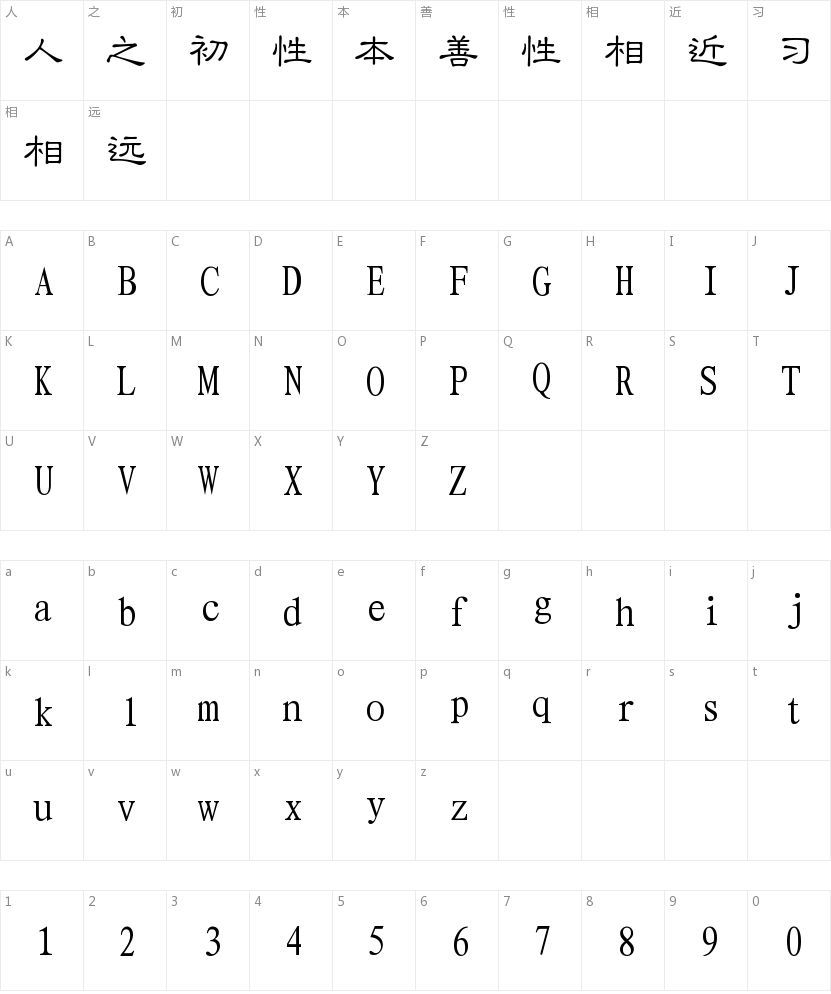
经典隶变
经典隶变字体是一种汉字字体,它的设计灵感来自古代汉字的结构和形式,在保持古典风格的同时,又有一定的现代感。经典隶变字体的字形比较粗犷,字体结构比较简单,字体之间的间距比较大,字体的笔画粗细比较均匀,字体的视觉效果比较稳定,整体显得比较端庄。经典隶变字体适用于品牌标识、书籍封面、文档排版等场景,具有较强的视觉冲击力,能够给读者带来良好的视觉体验。
经典隶变是一款非常不错的手写艺术字体,具有很好的视觉感,适合于文化类的宣传设计、商业类品牌的广告和产品包装设计以及个性化文字排版等较多场景。